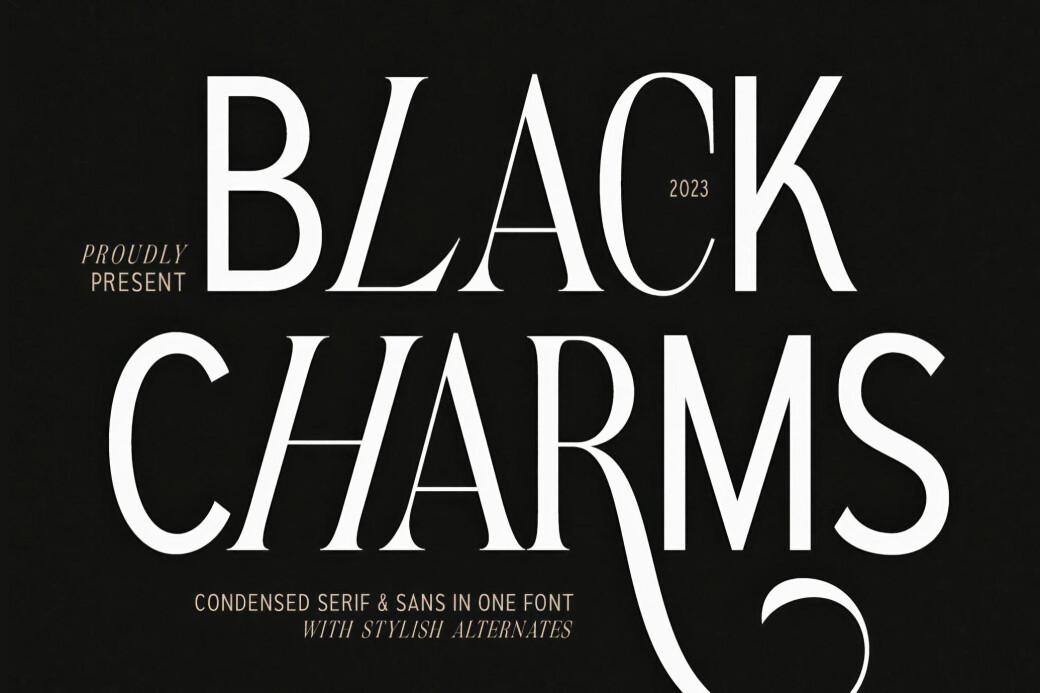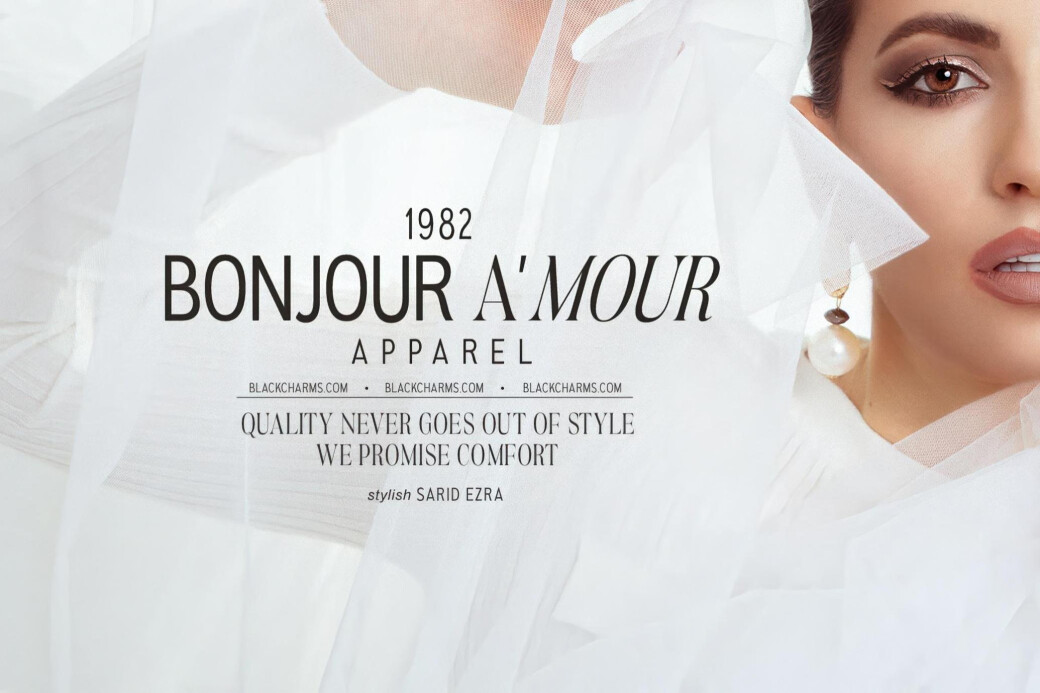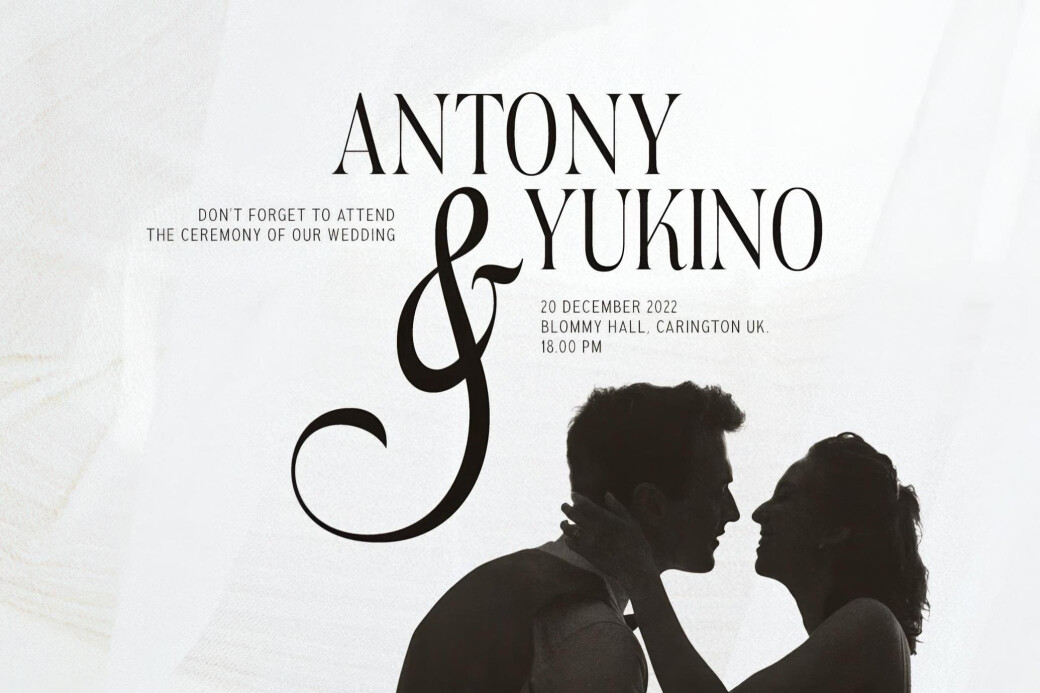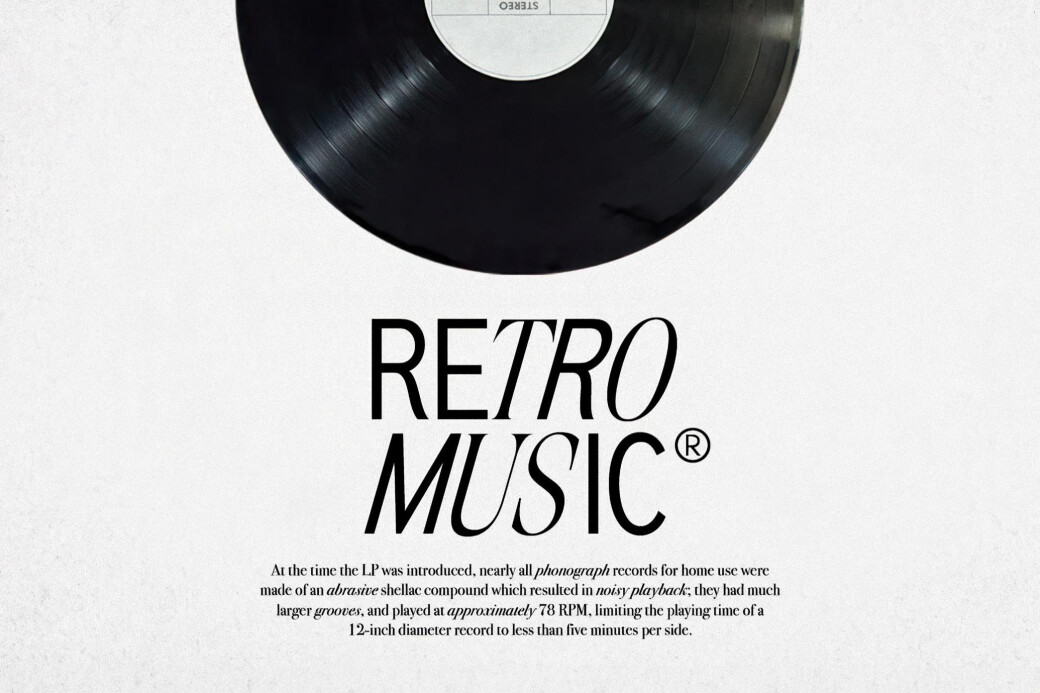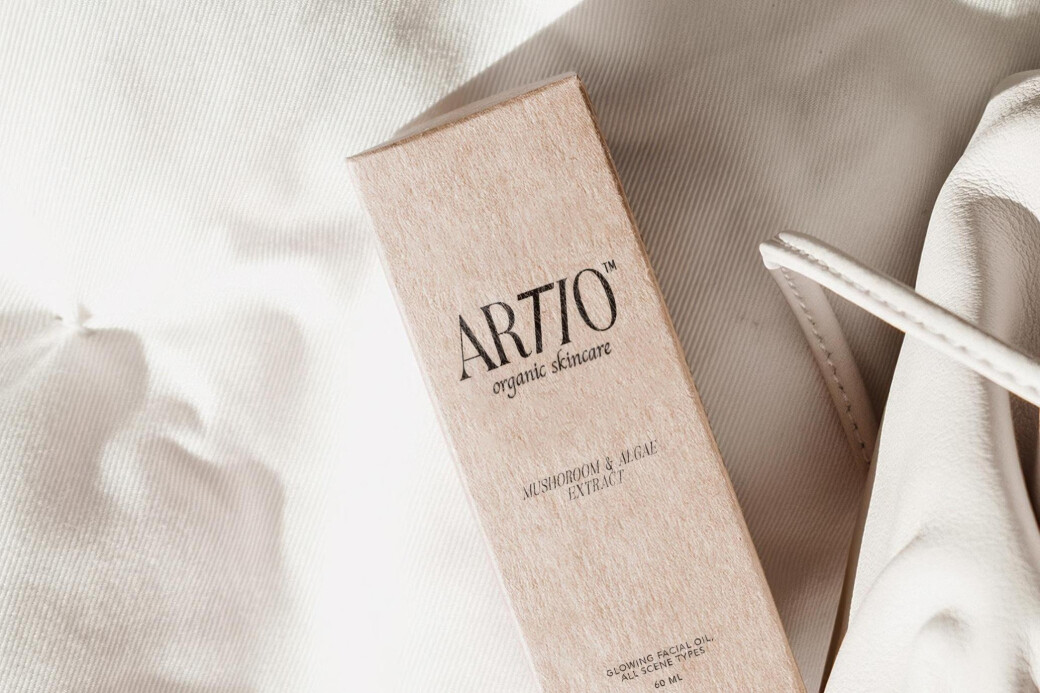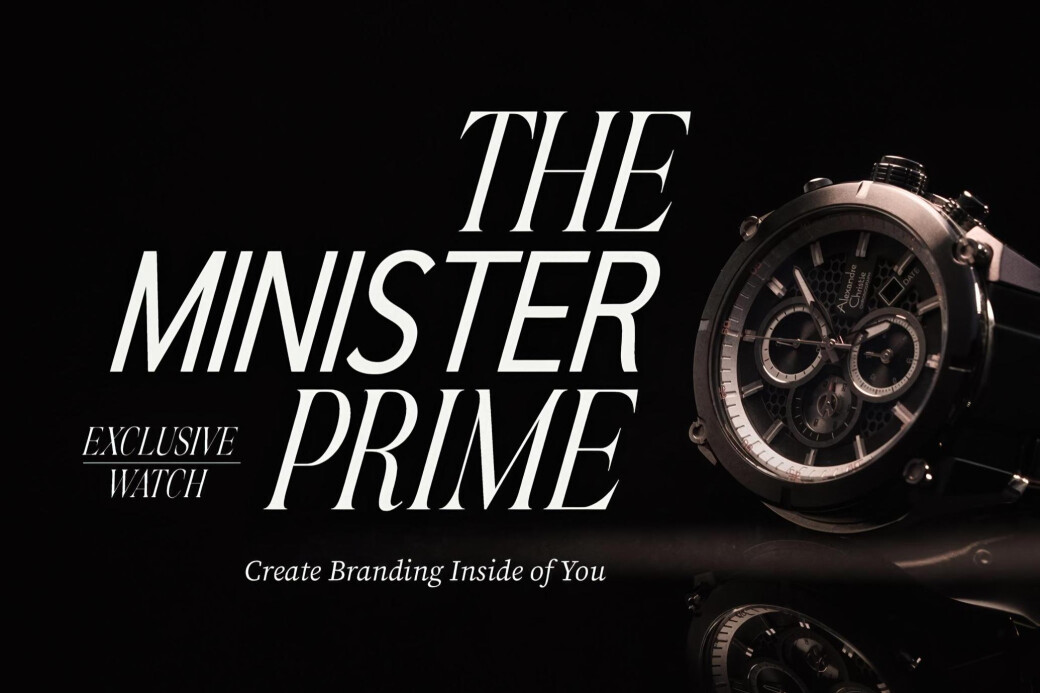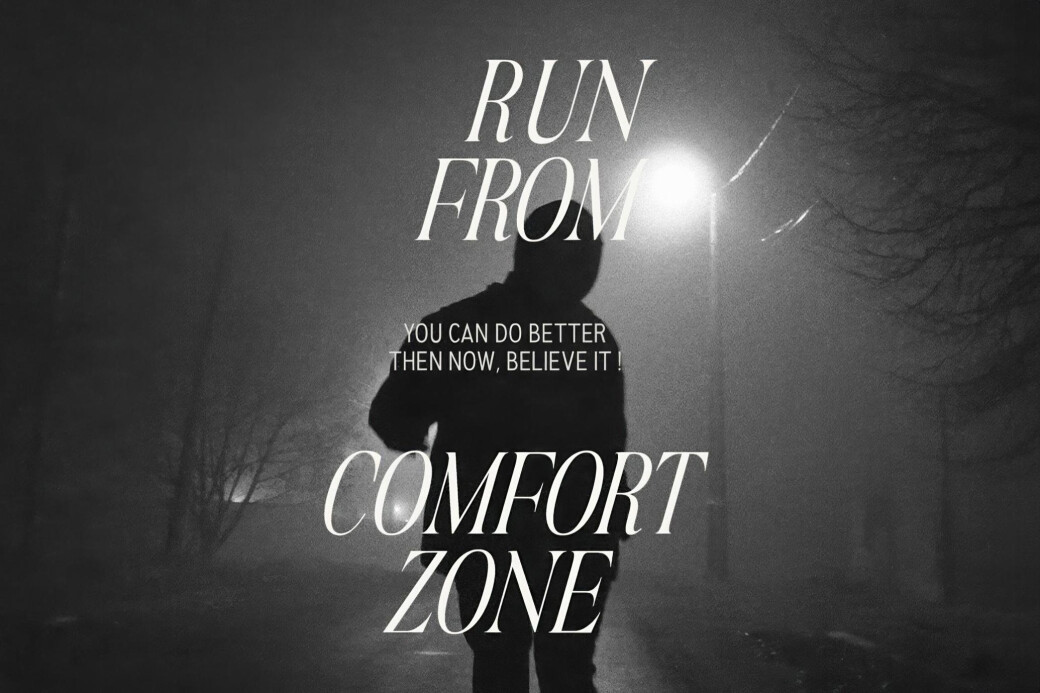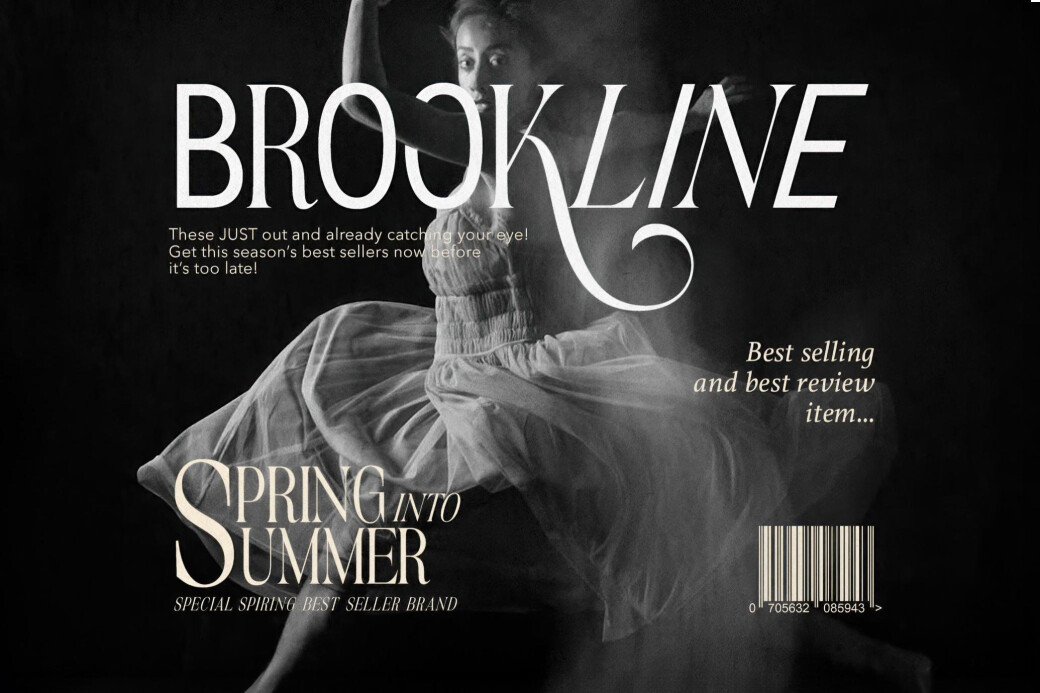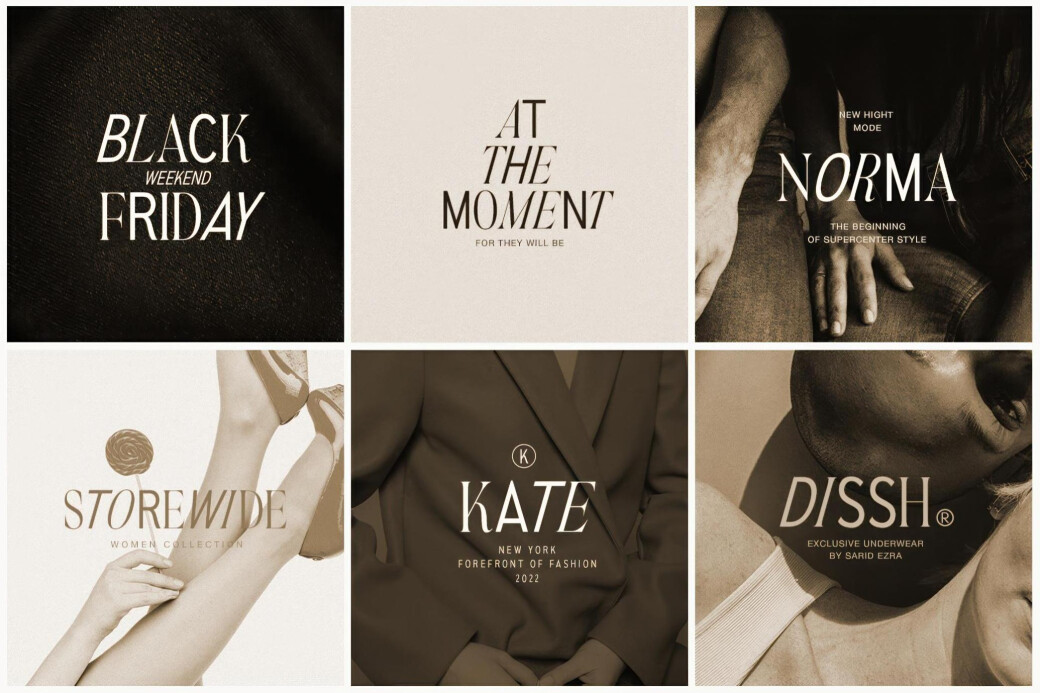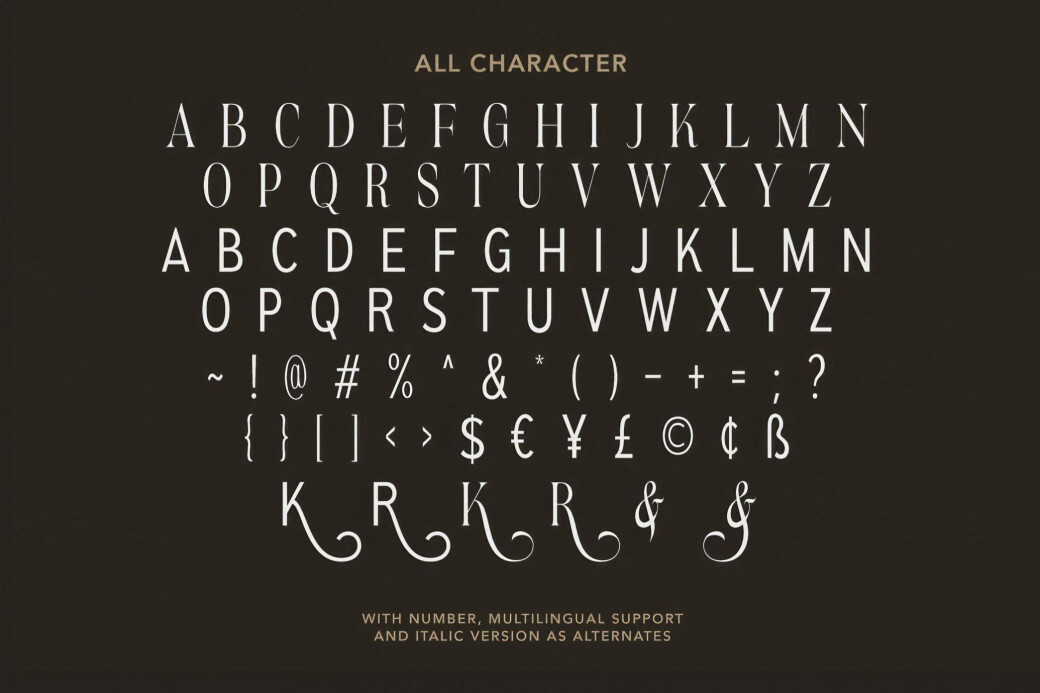
Мы обнаружили, что «Black Charms» — это стильное сочетание конденсированного серифа и современного безсерифного шрифта. Он создает впечатляющий баланс между изысканностью и актуальными трендами, что делает его идеальным выбором для высокомодных эстетик.
Дизайн с характером
Шрифт включает в себя сильные контрасты и острые серифы, а вытянутые формы букв напоминают о роскошном брендинге и редакционном дизайне. Безсерифный элемент добавляет чистоту и универсальность в композицию, что позволяет «Black Charms» использовать в журналах, логотипах и на упаковке.
И что особенно интересно — эта пара шрифтов в верхнем регистре также включает курсивную версию для альтернатив, что открывает новые возможности для смешивания шрифтов и стилей в ваших проектах.